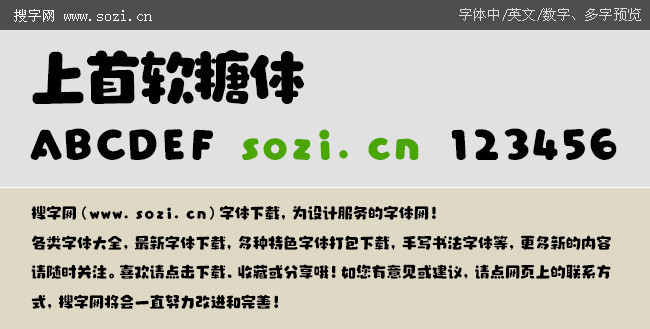
上首軟糖體
搜字網(wǎng)給大家提供一款上首軟糖體中文字體下載,上首軟糖體是上首字庫(kù)推出的一款非常可愛(ài)的藝術(shù)字體,字體多姿多態(tài),整體筆畫(huà)粗化處理,可愛(ài)萌動(dòng)圓潤(rùn)是此套字庫(kù)的亮點(diǎn)。可應(yīng)用于兒童包裝,卡通海報(bào),圖書(shū)封面等廣告設(shè)計(jì)。